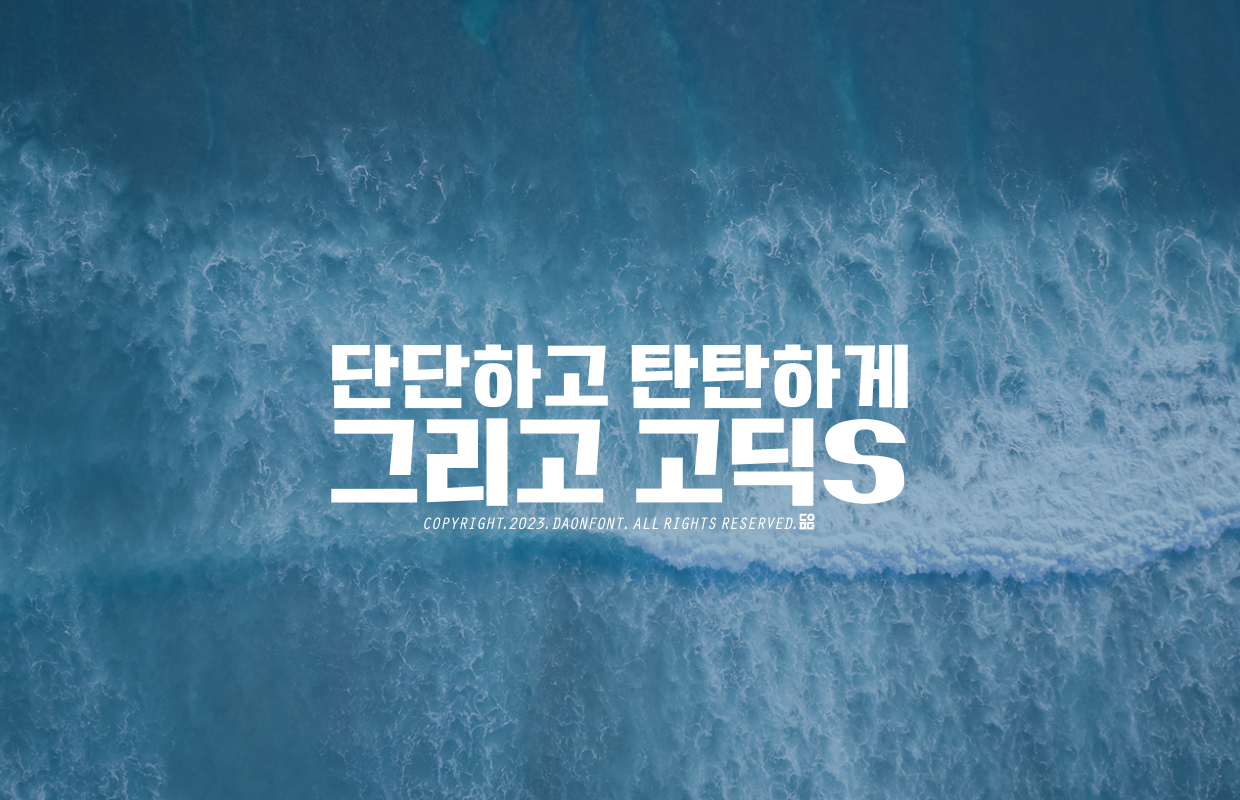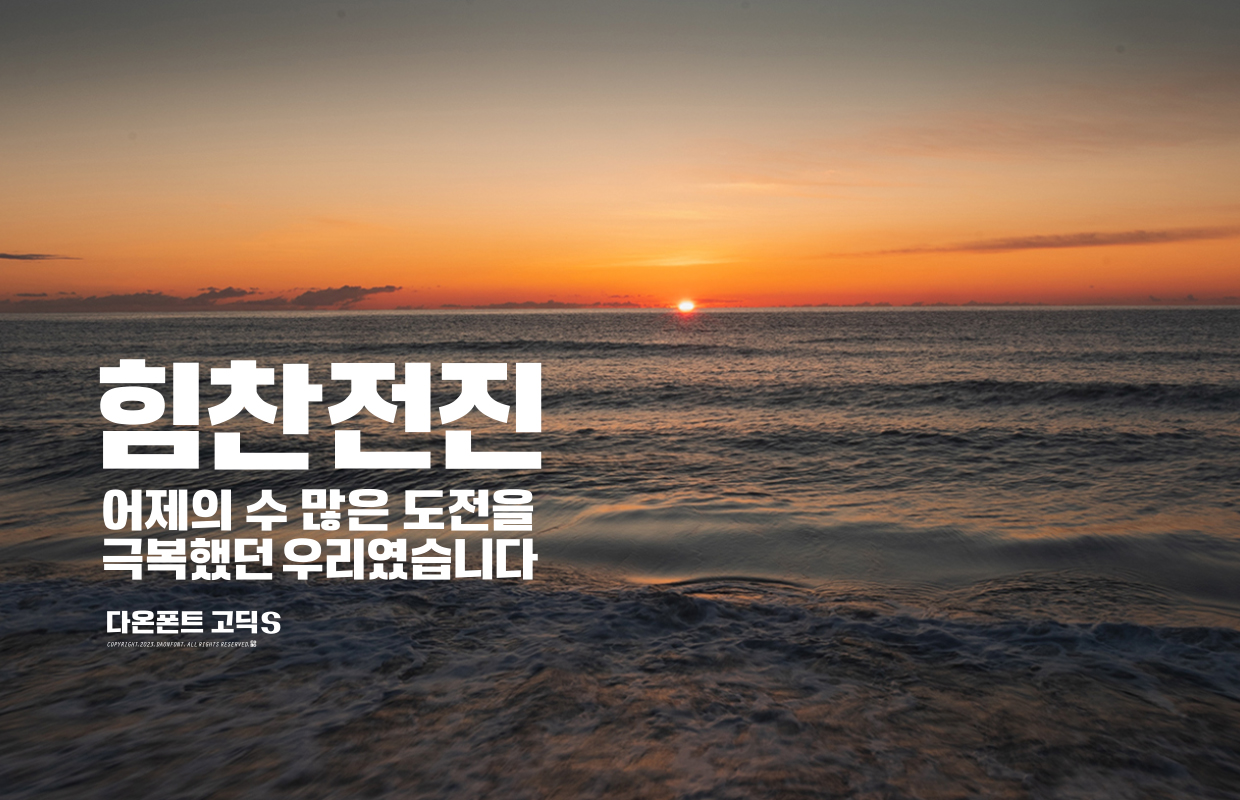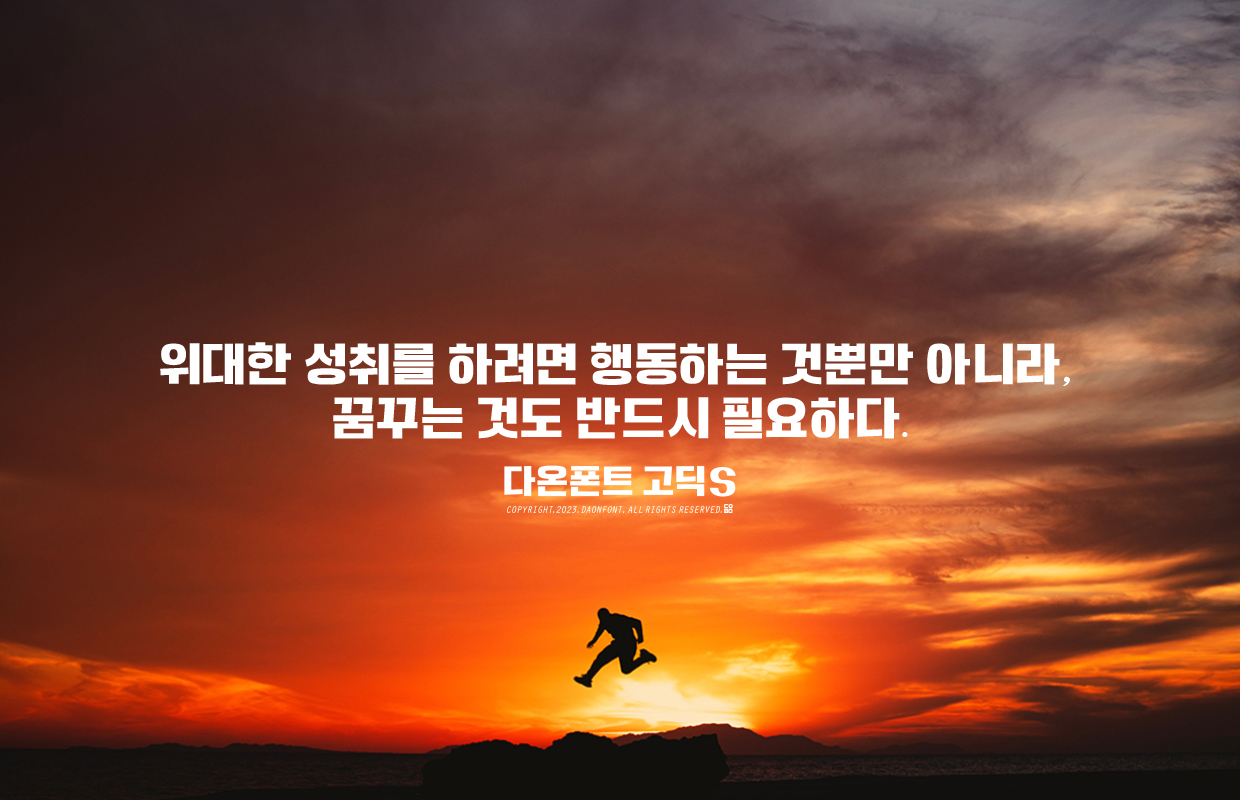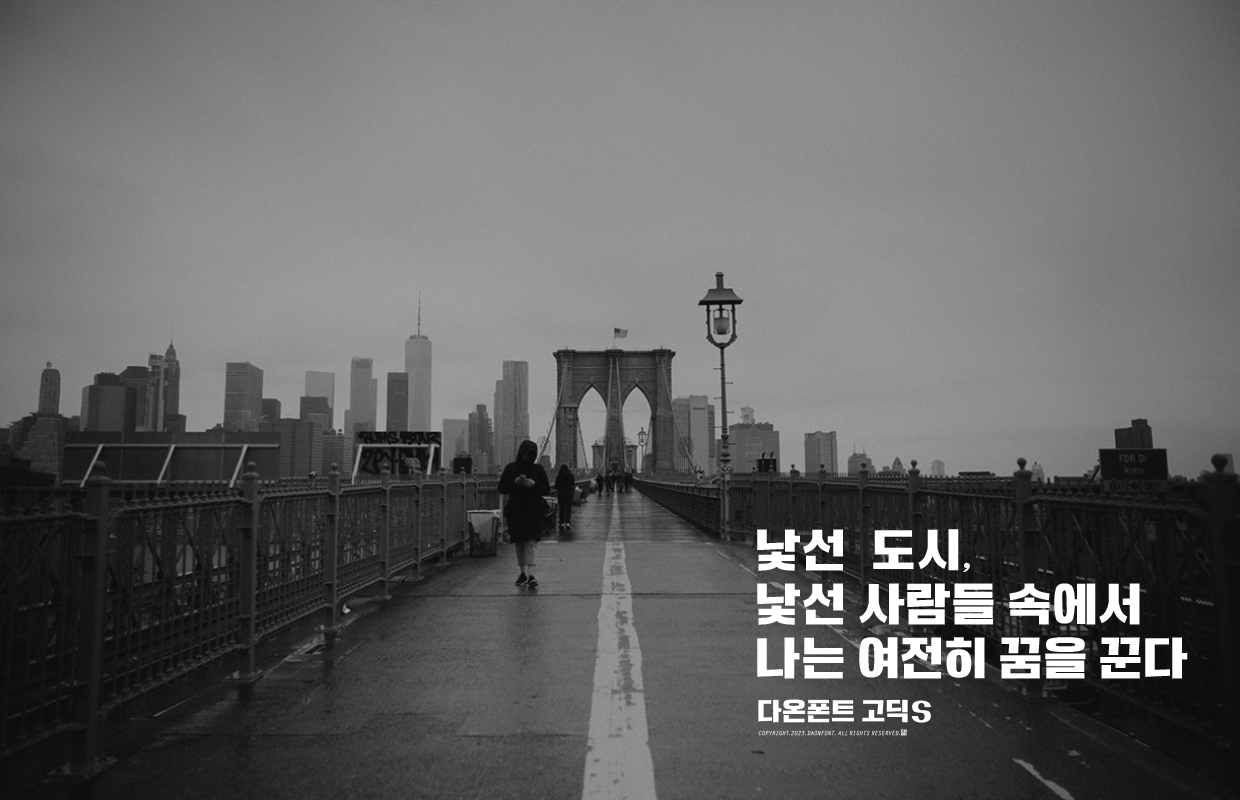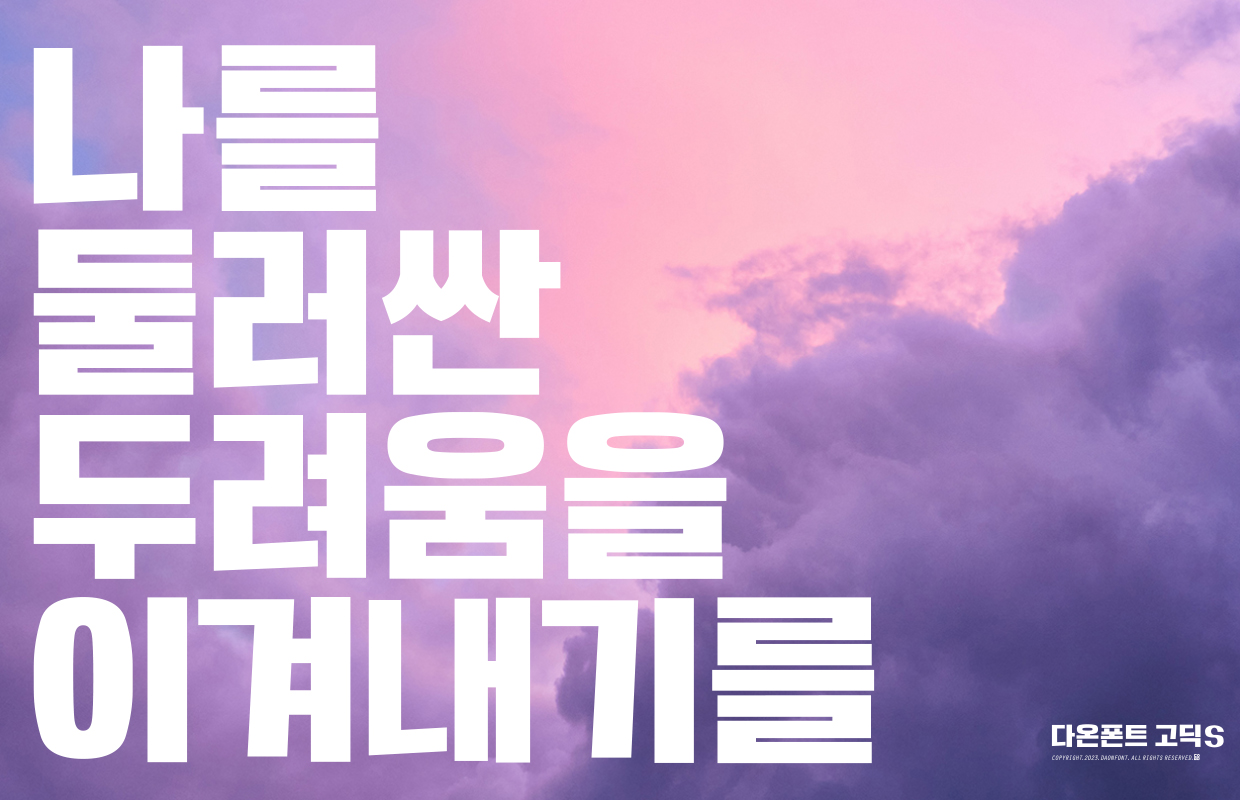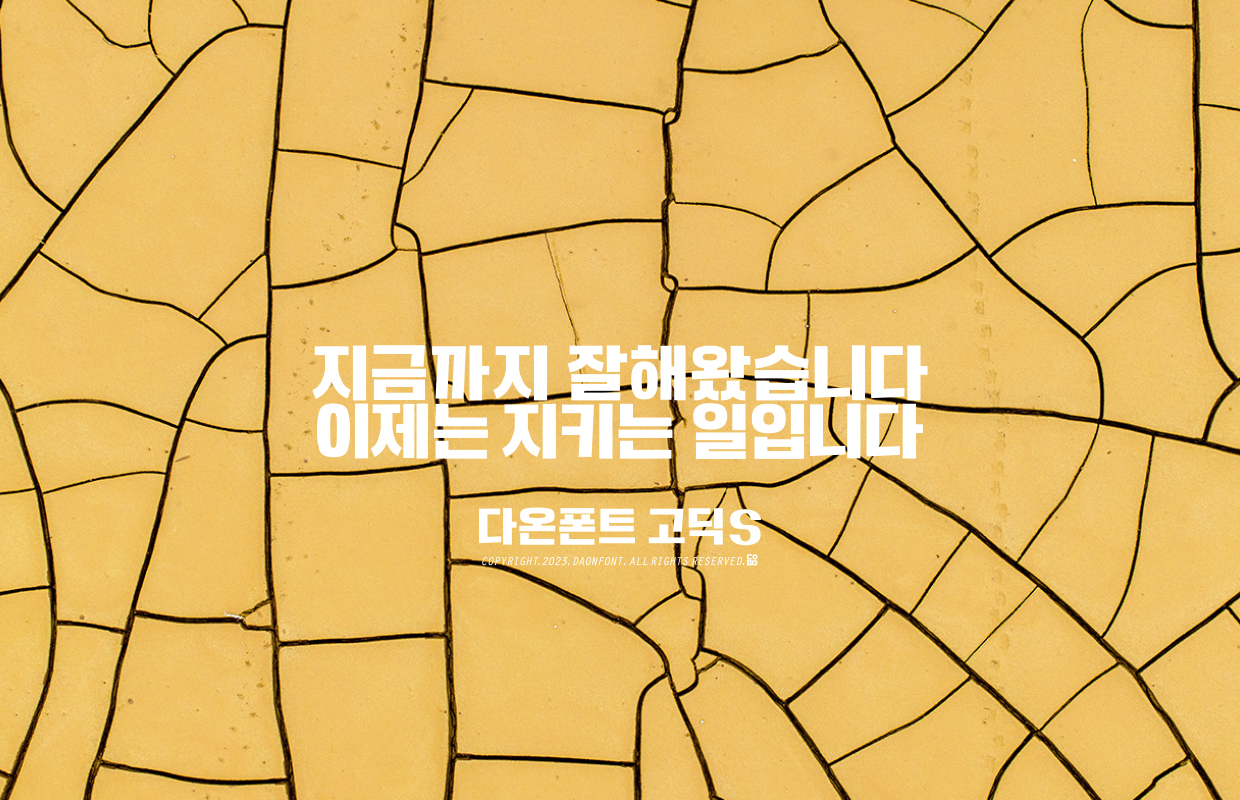
다온폰트 신서체 고딕S 출시예정 안내
다온폰트의 신서체,
고딕S가 출시될 예정입니다.
고딕S는 제목용 서체로 제작되어 두꺼운 획을 가진 서체입니다.
두꺼운 획들로 글자가 답답해 보이지 않도록
자소의 속공간을 넉넉히 만들어 글자의 가독성을 살린 서체입니다.
이번 출시될 예정인